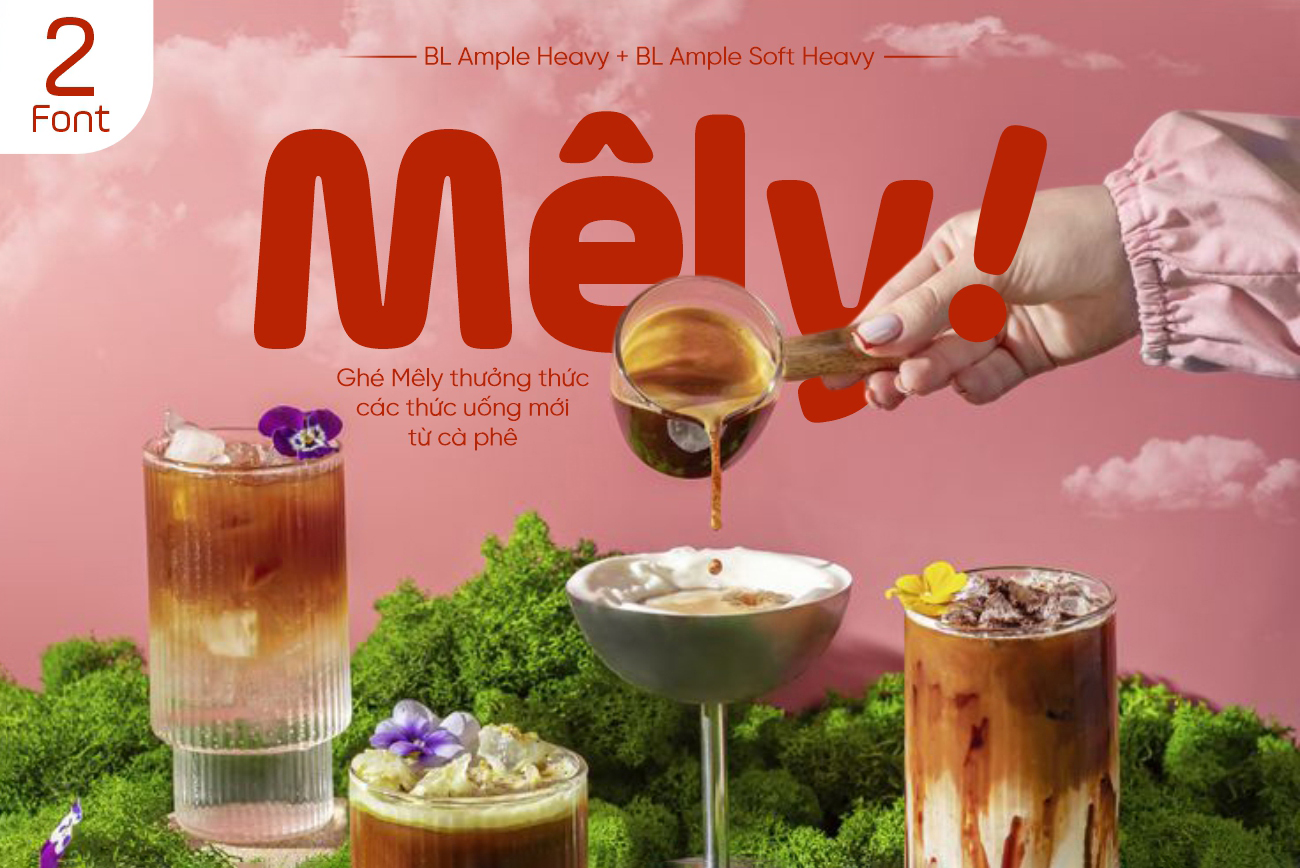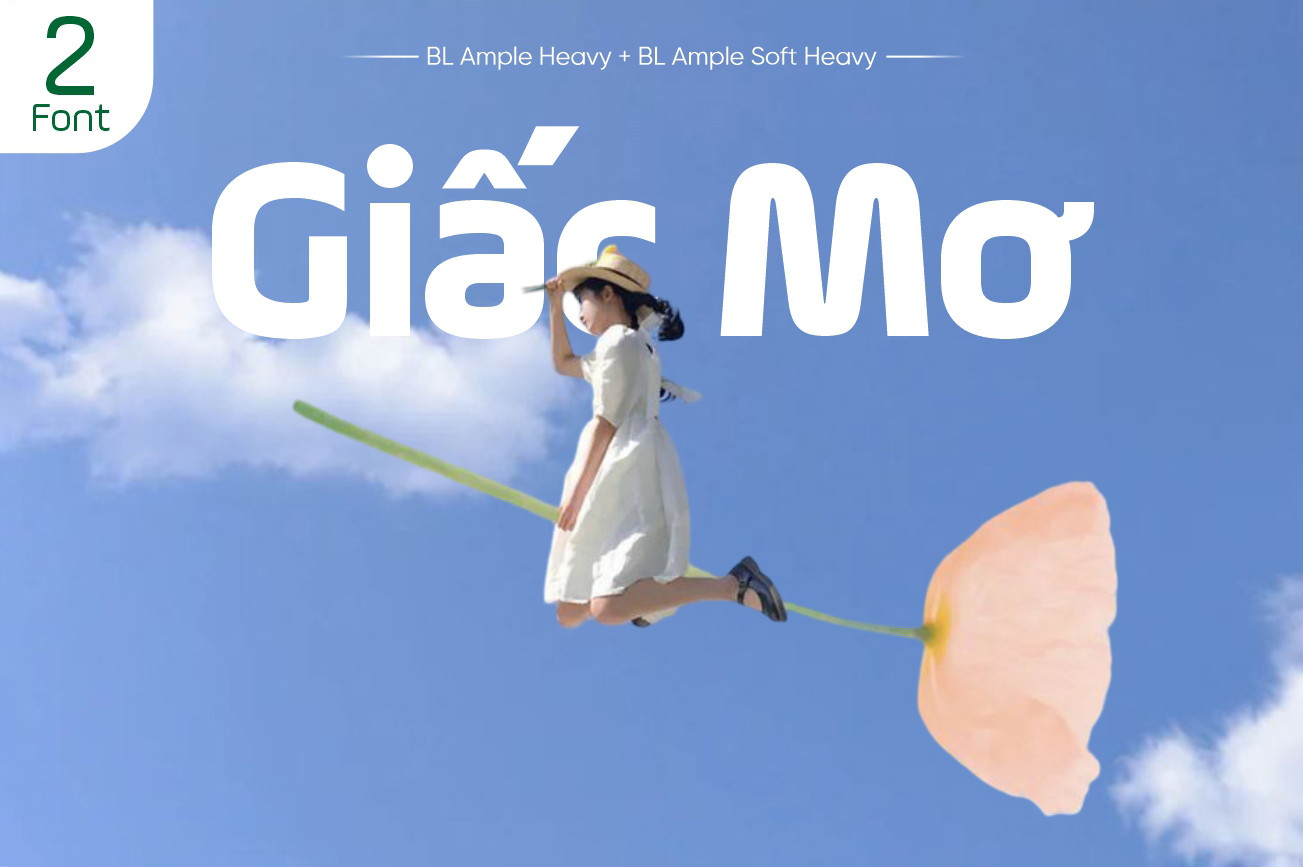
BL Ample Heavy + BL Ample Soft Heavy - Font công nghệ việt hóa
Tác giả Aakash Soneri
Việt hóa Font BL
BL Ample Heavy và BL Ample Soft Heavy là hai phiên bản Việt hóa từ weight heavy của bộ font Ample và Ample Soft do Aakash Soneri thiết kế, thuộc hệ font hiện đại được đánh giá cao về tính ứng dụng và khả năng hiển thị. Đây là những lựa chọn tiêu biểu trong nhóm font công nghệ việt hóa, được phát triển nhằm phục vụ nhu cầu trình bày mạnh mẽ, rõ ràng và nhất quán trong các thiết kế đương đại. Team BL đã thực hiện quá trình Việt hóa một cách cẩn trọng, tối ưu toàn bộ hệ thống dấu tiếng Việt để đảm bảo từng ký tự đều sắc nét, cân đối và giữ đúng tinh thần thiết kế gốc, giúp font dễ dàng sử dụng trong môi trường sáng tạo và truyền thông tại Việt Nam.
Về kiểu dáng, BL Ample Heavy sở hữu cấu trúc chữ dày, chắc, nét thẳng rõ ràng và hình khối ổn định, mang lại cảm giác mạnh mẽ, hiện đại và mang đậm hơi thở công nghệ. Trọng lượng heavy giúp chữ trở nên nổi bật hơn khi đặt trong tiêu đề, banner, poster hay các bố cục cần tạo điểm nhấn thị giác cao. Trong khi đó, BL Ample Soft Heavy vẫn giữ độ dày đặc trưng nhưng được bo tròn nhẹ ở các góc, tạo cảm giác mềm mại và thân thiện hơn, phù hợp với những thiết kế hướng đến trải nghiệm người dùng. Cả hai đều thể hiện rõ tinh thần của một font công nghệ việt hóa, vừa chuẩn mực, vừa linh hoạt trong ứng dụng thực tế.
Sự song song tồn tại của hai phiên bản heavy mang lại lựa chọn đa dạng cho nhà thiết kế. BL Ample Heavy phù hợp với các dự án công nghệ, startup, giao diện ứng dụng, website, dashboard hoặc hệ thống nhận diện thương hiệu cần sự cứng cáp và dứt khoát. BL Ample Soft Heavy lại phù hợp với các sản phẩm số, nội dung truyền thông, ấn phẩm marketing hoặc thiết kế cần sự thân thiện nhưng vẫn giữ được độ mạnh cần thiết. Nhờ khả năng hiển thị tốt ở nhiều kích thước và môi trường khác nhau, cả hai font đều đáp ứng tốt yêu cầu của các dự án hiện đại.
Nguồn gốc của weight heavy trong họ font Ample và Ample Soft xuất phát từ nhu cầu mở rộng khả năng sử dụng của bộ chữ trong các bố cục đòi hỏi sức nặng thị giác cao. Khi được Team BL Việt hóa thành BL Ample Heavy và BL Ample Soft Heavy, hai font không chỉ giữ nguyên triết lý thiết kế của Aakash Soneri mà còn trở nên phù hợp hơn với người dùng Việt. Nếu bạn đang tìm kiếm một font công nghệ việt hóa có độ dày ấn tượng, rõ ràng và dễ ứng dụng cho nhiều nền tảng thiết kế khác nhau, đây sẽ là lựa chọn đáng tin cậy để nâng cao tính chuyên nghiệp và hiệu quả thị giác cho mọi dự án.